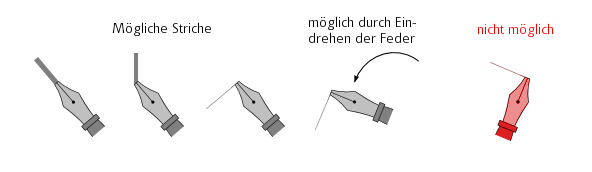
Schrift aber welche
Die ganze Dick-dünn-Verteilung klassischer Schriften richtet sich nach dem Linienzug der Breitfeder:
Die Fabiol folgt auch diesem klassischen Duktus:
Einzige Ausnahme ist der unpassende Strich am k, der damit einfach nicht zum Rest der Schrift paßt.
Die Chesterfield kann man so einfach nicht damit vergleichen.
Genau darauf wollte ich hinaus! Entweder vollkommen konsistent wie eine klassische Schrift mit Breitfederduktus oder aber richtig dekorativ. Und bei einer Dekoschrift dann zB auch konsequent alle(!) Serifen falschgeschrägt ausführen. Also entweder eine richtige Garamond oder die Chesterfield.
Entweder vollkommen konsistent wie eine klassische Schrift mit Breitfederduktus oder aber richtig dekorativ.
Ihr denkt zu theoretisch. Wie bereits angemerkt handelt es sich ja um eine Druckschrift, nicht um eine handgeschriebene. Wie würdest Du die unten gezeigten Glyphen (das a ist nur zum Vergleich) aus der Garamond mit der Breitfeder schreiben?
Die beiden Z lassen sich doch ohne Probleme anhand der oben von mir gezeigten Federstriche erklären.
Mathematische Zeichen sind in Druckschriften seit jeher geometrisch konstruiert und somit unabhängig vom normalen Buchstabenduktus.
Bleiben die Guillemets. Bei denen wäre ja tatsächlich zu erwarten, daß die obere Linie dicker ist. (Hier ist zu sehen, daß das Zeichen ursprünglich auch so ausgesehen hat.) Vielleicht handelt es sich bei der heute üblichen dünnen Form um eine optische Korrektur, damit das kleine Zeichen nicht zu dick aussieht oder die Striche beim Druck zusammenlaufen, aber da kann ich nur vermuten. (Schreiben könnte man es wohl auch mit der Federkante.)
… Bleiben die Guillemets. Bei denen wäre ja tatsächlich zu erwarten, daß die obere Linie dicker ist. …
dicker? Doch nur bei Linkshändern. Bei Rechtshändern wäre die obere Linie dünner.
Die beiden Z lassen sich doch ohne Probleme anhand der oben von mir gezeigten Federstriche erklären.
Müsste man nicht, um diese dicke Diagonale hinzukriegen, seine Hand als rechtshänder genau so "verdrehen" wie oben rot markiert?
Die ganze Sache mit dem Dukus ist bei Druckschriften nicht mehr immer 100% nachvollziehbar ...
Das Z war mal der Form nach eher ein I mit Querbalken oben und unten, bei dem die (normal breite) Senkrechte irgendwann schräg gestellt wurde und dabei die Strichstärke übernommen wurde, auch wenn der Duktus einer Feder eine dünnere Linie gebieten würde.
Analog dazu hat das M links eine dünne Senkrechte, rechts eine normal-breite – weil die Senkrechten früher mal schräg waren und das weiter so übernommen wurde, auch wenn die Feder das nicht so machen würde.
(Was jetzt alles nicht heißt, dass nicht die Serife des k bei der Fabiol tatsächlich einfach seltsam ist ... Nur ist auch die Fabiol halt keine Federzugschrift mehr, sondern eben gezeichnet. Ob sie also noch komplett dem Federduktus folgt oder eben für ihre Eigenheiten und Sonderlichkeiten ausbricht, liegt in der Entscheidungsfreiheit des Gestalters.)
nachdem ich einen Hinweis bekommen habe, dass in diesem Forum so trefflich über meine Schrift debattiert wird, möchte ich gerne aus Entwerfer-Sicht einen Beitrag leisten.
Da sich die Debatte vor allem am kleinen k entzündet hat, möchte ich gerne ein paar Hintergründe auch dazu kundtun.
Zunächst aber ein paar grundsätzliche Dinge zu meiner Herangehensweise, die dazu beitragen könnten, Licht auf einige formale Aspekte zu werfen:
Die Fabiol hat viele Väter/Mütter – will heissen, die Schrift basiert auf Einflüssen einer Reihe unterschiedlicher "Vorbilder" (im wahrsten Sinne des Wortes), die sowohl zeitlich als auch räumlich verschiedenen Quellen zuzuordnen sind. Sie bewegen sich etwa vom Ausgang des 15. bis zum Beginn des 17. Jahrhunderts, vom italienischen über hauptsächlich den französischen bis hin zum niederländischen und sogar englischen Raum.
Manche Buchstabenformen darf man sogar gewissermaßen als "Hommage" an einen bestimmten Entwerfer und sein Werk verstehen. Man betrachte etwa das Versal C und schlage in der berühmten ersten Ausgabe der Hypnerotomachia Poliphili von 1499 nach, und man wird feststellen, dass es mir diese spezielle Letter des Francesco Griffo angetan hat. Aber auch Garamond lässt sich finden, Geoffroy Tory etwa oder bei der Kursiven sicherlich Robert Granjon. Daneben noch eine Reihe namenloser oder nicht gesicherter Originalquellen.
Nun warum dies – meine These dazu lautet: Weil alle diese Menschen und Typen etwas miteinander zu tun hatten, oft sogar ganz real und physisch – Garamond etwa besaß mit einiger Sicherheit Matrizen von Griffo, er und Geoffroy Tory kannten sich sogar persönlich. Aber am wichtigsten: alle haben sie voneinander "abgekupfert", und zwar mit bestem Wissen und Gewissen und in der Absicht, an einem großen Ganzen mitzuarbeiten, es zu variieren und zu verbessern. Ein "Copyright" oder die individuelle Abgrenzung der Personen untereinander und zu ihrem Werk gab es nach meiner Erkenntnis damals nicht, eine derartige Auffassung wäre auch mit dem Gedanken des Humanismus nicht vereinbar gewesen.
Kurz nachgegoogelt im Internet fand ich nur eine nennenswerte Übereinstimmung zu Fabiol (ich habe kurzer Hand auf das e am Schluss verzichtet, da man es im deutschsprachigen Raum wohl meist falsch, nämlich ausgesprochen hätte): eine Hirtenflöte von den Balearen, ein wohl kaum mehr benutztes uraltes Instrument, trägt den selben Namen.
Ich fand diese Koinzidenz sehr angenehm, weil poetisch, skurril und auch irgendwie angenehm erdverbunden.
Dann ging es eben sofort in die Post und der Name war in der Welt …